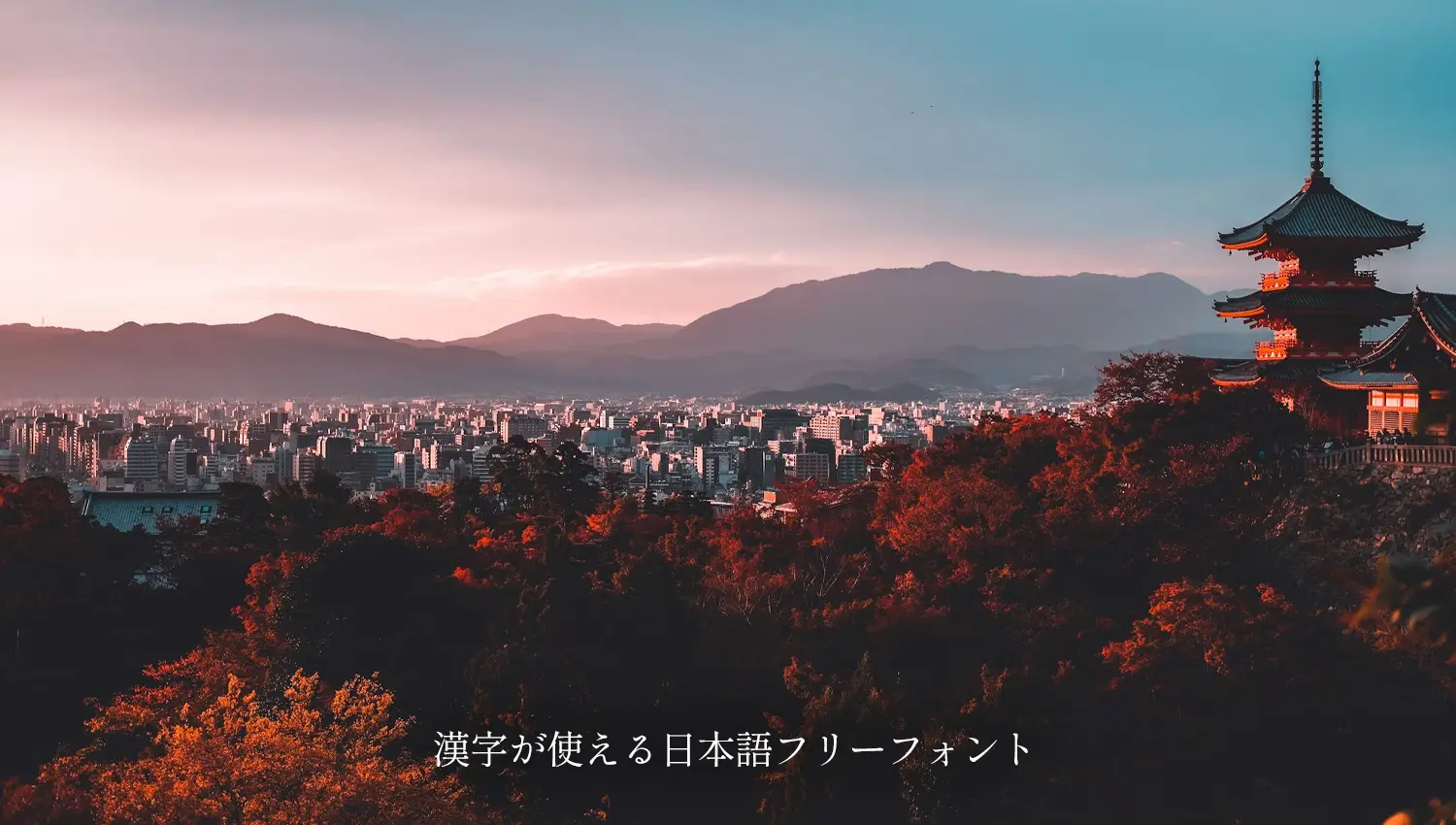
漢字が使える日本語フリーフォント97選(商用利用可)
【無料】漢字が使える日本語フリーフォント
ロゴデザイン、印刷物デザイン、Webサイトのイメージを制作する際に、日本語フォントのバリエーションがもっとあったらと思うこともしばしば…
探してみると、漢字も使える魅力的な日本語のフリーフォントもかなり増えてきました。そこで今回は、幅広く活用できる(商用可・無料)おすすめの日本語フォントをゴシック体・明朝体・毛筆体・手書き風・デザイン(かわいい・おしゃれ)と勝手にカテゴライズして紹介します。
ゴシック体フォント
Noto Sans Japanese
Googleフォントのポピュラーなゴシック体。
BIZ UDPゴシック
読みやすさとデザインバランスに優れたモリサワのユニバーサルデザインフォント。
Murecho
ニールサマーアワとポジタイプによって作成されたゴシック体フォント。9つの実用的なウェイトと可変フォントで利用できます。
ZEN角ゴシック
クラシックでありながらシンプルな可読性に優れたゴシック体フォント。
ZEN丸ゴシック
コーナーに深みを入れ自然な柔らかさを感じられるよう設計された、おしゃれで可愛らしい丸ゴシック体フォント。
ロゴたいぷゴシック
病院や幼稚園などのやわらかいイメージのロゴなどにバランス良く映えるエレガントなフリーフォント。
やさしさゴシック
丸文字とまではいかないが少し丸みを帯びたやさしいイメージの読みやすいフォント。
フロップデザインフォント
水平、垂直の線がデザインの基本となっているバランスの取れた使いやすいゴシック体フォント。
スマートフォントUI
スマートなデザイン(縦長)のフォント。漢字に対して仮名文字がこぶりになってるトコが特徴のおしゃれフォント。
コーポレート・ロゴ
企業やサービスで使われているようなモダンでシンプルなロゴ文字をイメージしたフリーフォント。
東青梅ゴシック
「M+ OUTLINE FONTS」と「梅Pゴシック」をベースに、よく使用される漢字の字形をより統一したフォント。
ぼくたちのゴシック
ちょっと太めで、丸みのある子供っぽい書体の日本語フリーフォント。
せのびゴシック
M+ FONTSの幅を縮めた縦長(背伸び)でテクノっぽいかっこいいフォント。
JKゴシックL
女子高生が書いたような丸みのある、かわいい系日本語フリーフォント。
刻ゴシックフォント
スタンダードなゴシック体の漢字フォントに、それとは相反する字面の小さなひらがな・カタカナを合成した日本語フォント。
Rounded M+
M+ OUTLINE FONTSをもとに、形状を加工する処理を施して丸ゴシックにした日本語フォント。豊富なウェイトが魅力。
マメロン
「まるもゴシック」というかなフォントにマキナス Scrap[5]の漢字と記号に丸型処理を施し合成したかわいいフォント。
源暎Nuゴシック
漫画の強調セリフとして使えるよう源ノ角ゴシックを改変したゴシック体。タイトルなどにも使用できそうな大振りな仮名が特徴の特太フォント。
ほのか丸ゴシック
特徴のある柔らかな曲線が印象的な丸ゴシック体。かな文字は小さめにデザインされた綺麗なフリーフォント。